本記事では、スマートな印象を演出できる、スリムで長体スタイルの日本語フリーフォントをまとめてみました。
スタイリッシュで洗練された雰囲気を出したいときに活躍するのが、縦にすらっと伸びた細身のフォント。限られたスペースでも情報を詰め込みやすく、スタイルを崩さずに収まりよく見せることができます。ファッション系のビジュアルや都会的な雰囲気のLP、タイトルやキャッチコピーの装飾などにもぴったりです。
今回は、シャープで都会的な印象を与えるスリム&長体の日本語フリーフォントを厳選してご紹介。洗練されたスマートなデザインを目指す方は、ぜひ参考にしてみてください。
スマート!スリムで長体スタイルのおすすめ日本語フリーフォント
バナナスリップ
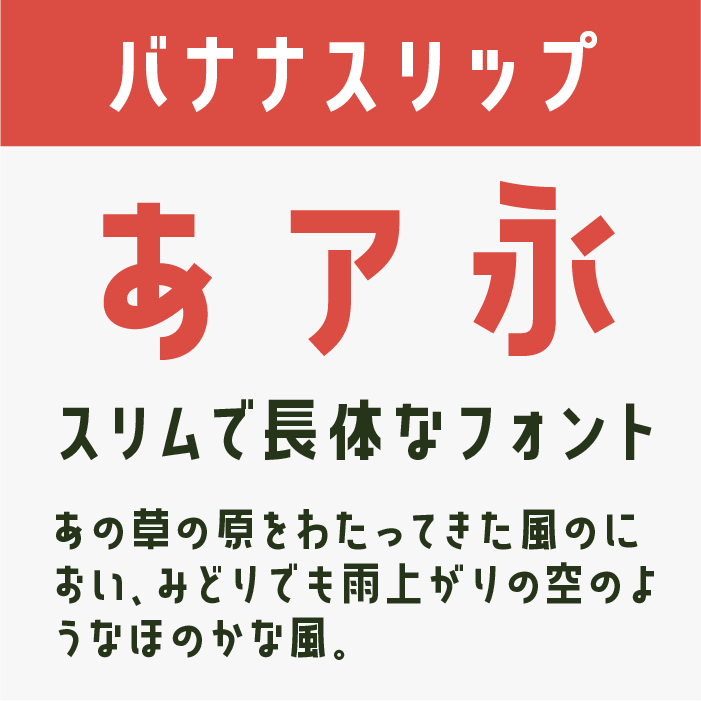
「バナナスリップ」フォントは、やわらかさと軽やかさが共存した、親しみやすい印象のフォントです。スリムで縦長な形状が視線を上に導き、タイトルや見出しに使うと洗練された軽快さを与えてくれます。
黒薔薇シンデレラ
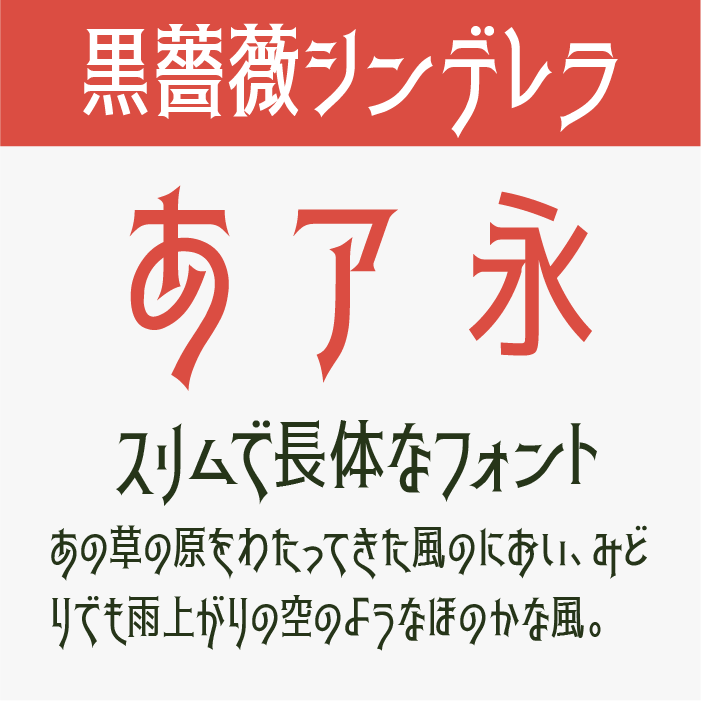
「黒薔薇シンデレラ」フォントは、繊細で優雅な雰囲気をまとったスリム系フォントです。縦のラインがしなやかに伸び、ほんのりクラシカルな装飾がドラマチックな世界観を演出します。ロマンチックな場面にぴったりなフォントです。
せのびゴシック
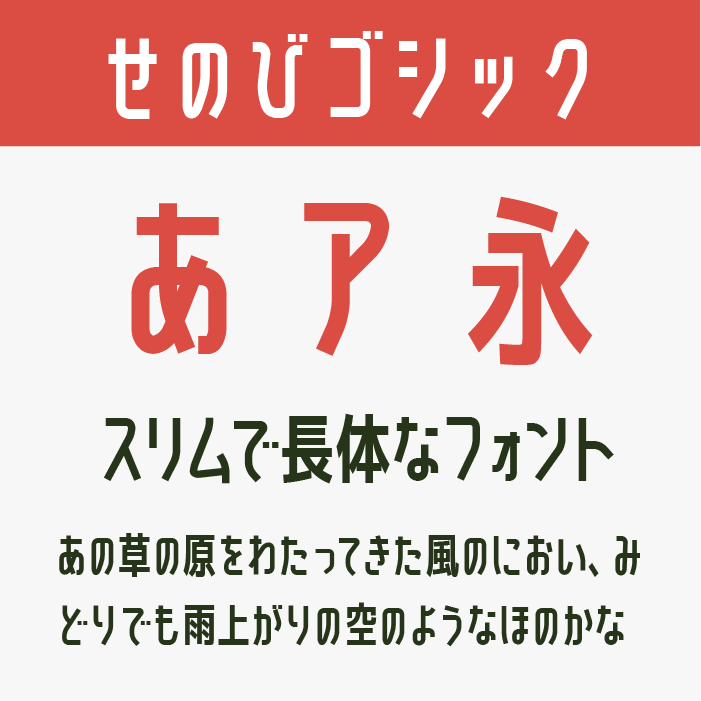
「せのびゴシック」フォントは、素朴さとスマートさを絶妙にブレンドしたフォントです。細身ながら安定感があり、情報をしっかりと伝えたい場面にも向いています。自然体な中に芯の強さを感じるデザインです。
Smiley Sans
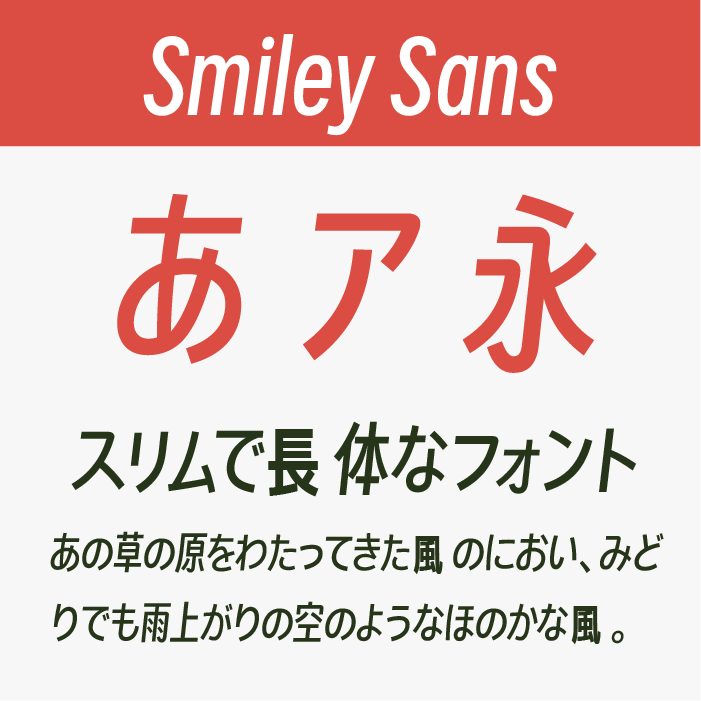
「Smiley Sans」フォントは、モダンで明るい印象を持つサンセリフ体です。スリムなフォルムと自然な丸みが特徴で、読みやすさと軽快なデザイン性を両立しています。ポジティブなトーンのデザインにおすすめです。
きんいろサンセリフ
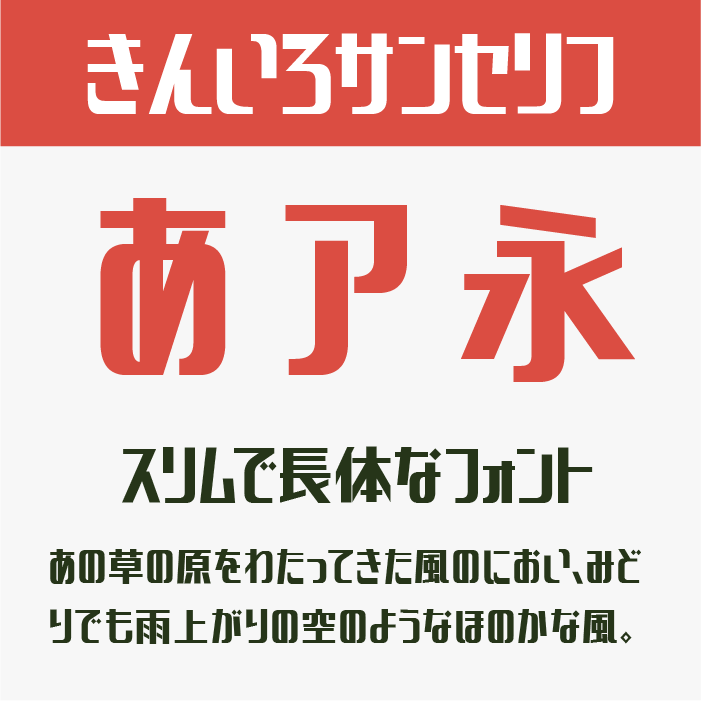
「きんいろサンセリフ」フォントは、力強さとスマートさを兼ね備えた縦長スタイルのフォントです。スタイリッシュでありながらしっかりとした骨格があり、ブランドロゴやキャッチコピーに存在感を与えてくれます。
夜すがら
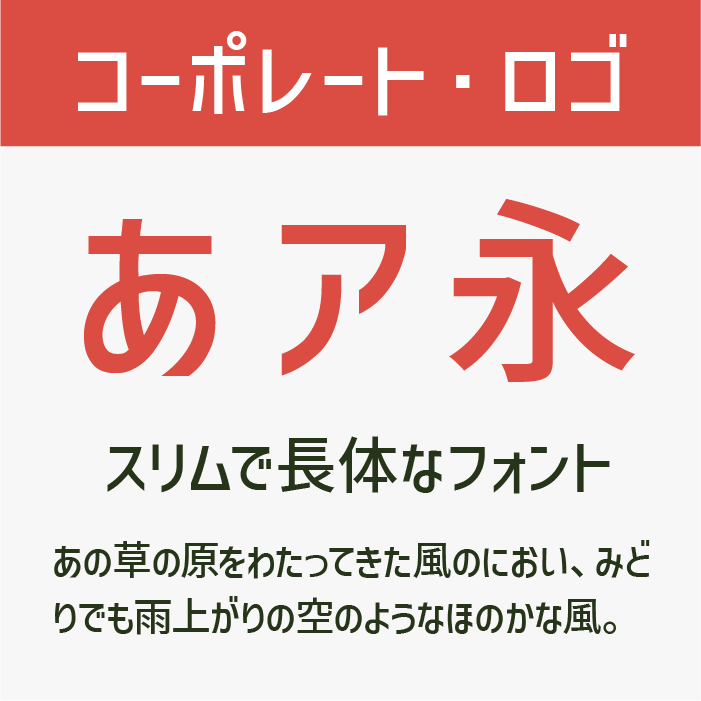
「コーポレート・ロゴ」フォントは、ビジネスシーンにフィットする信頼感のあるデザインが特徴です。スリムでありながら、丸みのあるディテールが程よく親しみやすく、コーポレートブランディングに適したバランス感を持っています。
ヒカリノカナ荒
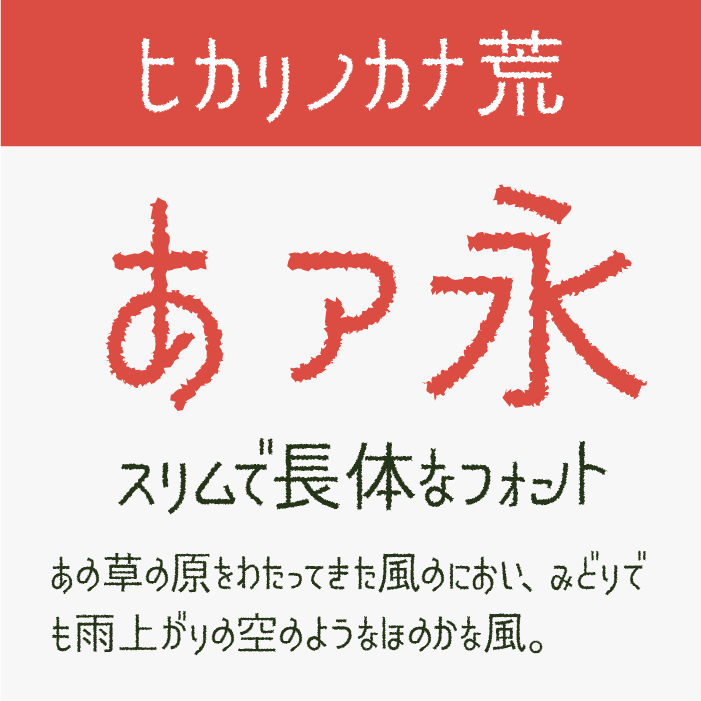
「ヒカリノカナ荒」フォントは、手書き風のざらつきと、縦長なスタイルが独特の風合いを生むフォントです。ナチュラルで優しい空気感と、かすれたテクスチャが相まって、どこかノスタルジックな味わいが広がります。